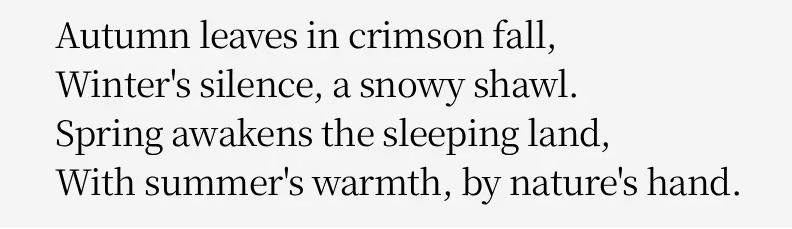
Source Serif 是 Adobe 字体团队在2014 年发布的一款开源衬线字体,属于 Adobe Originals 系列,也是思源宋体的西文组成部分。该字体由著名设计师 Frank Grießhammer 主导设计,灵感源自 19 世纪法国字体设计师 Firmin Didot 所代表的现代衬线体(Modern Serif),具有高对比度、垂直应力等风格特点。
Source Serif 提供从 ExtraLight 到 Black 共 9 档字重,支持 Condensed 与 Extended 变体(部分版本含斜体),覆盖拉丁文、希腊文、西里尔文等多种书写系统。开放的字腔设计让其在低分辨率或小字号下也能保持清晰,显著提升了长文本阅读的体验,所以在 ePub、PDF 等固定版式文档的正文中应用较为广泛,而Black 或 Bold 字重同样适用于品牌 Logo、杂志封面、宣传册标题等场景。